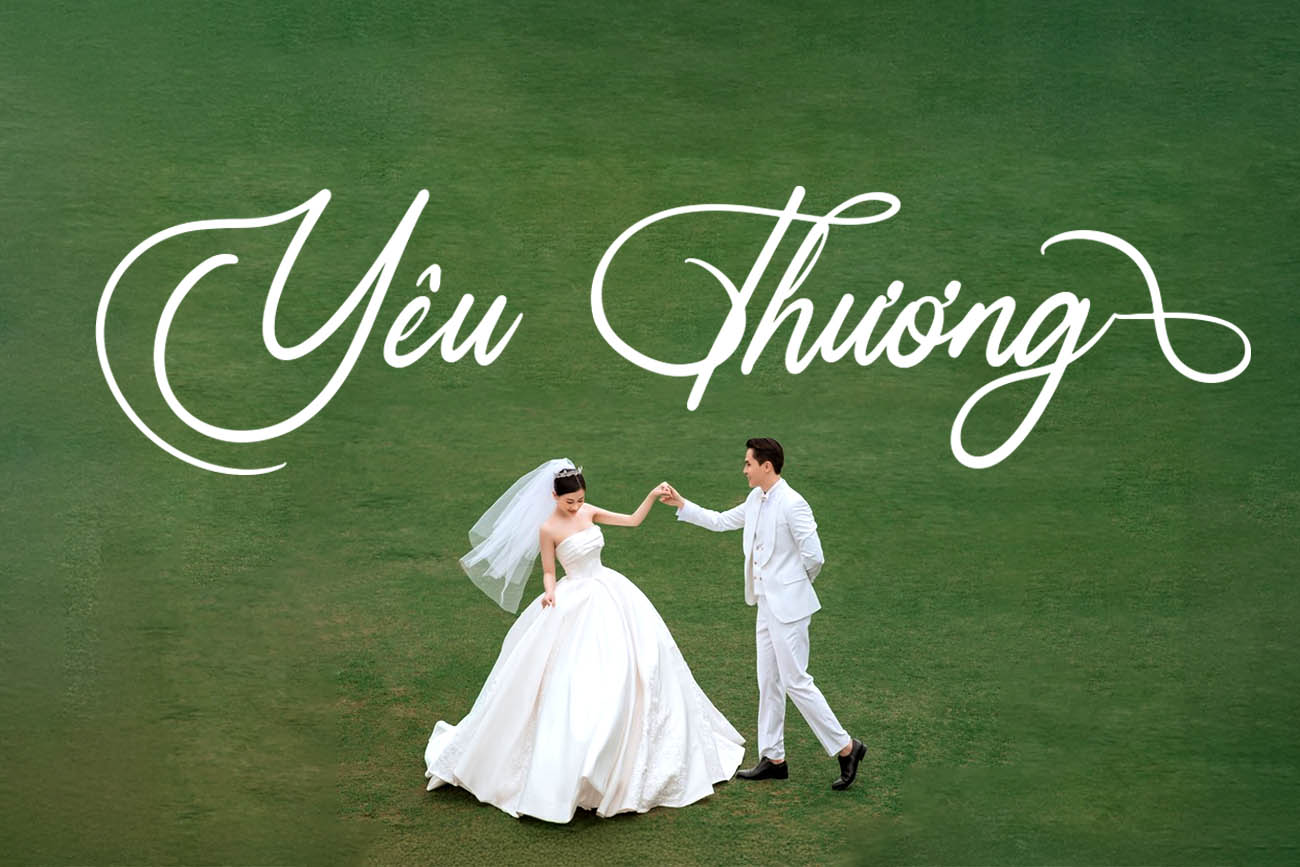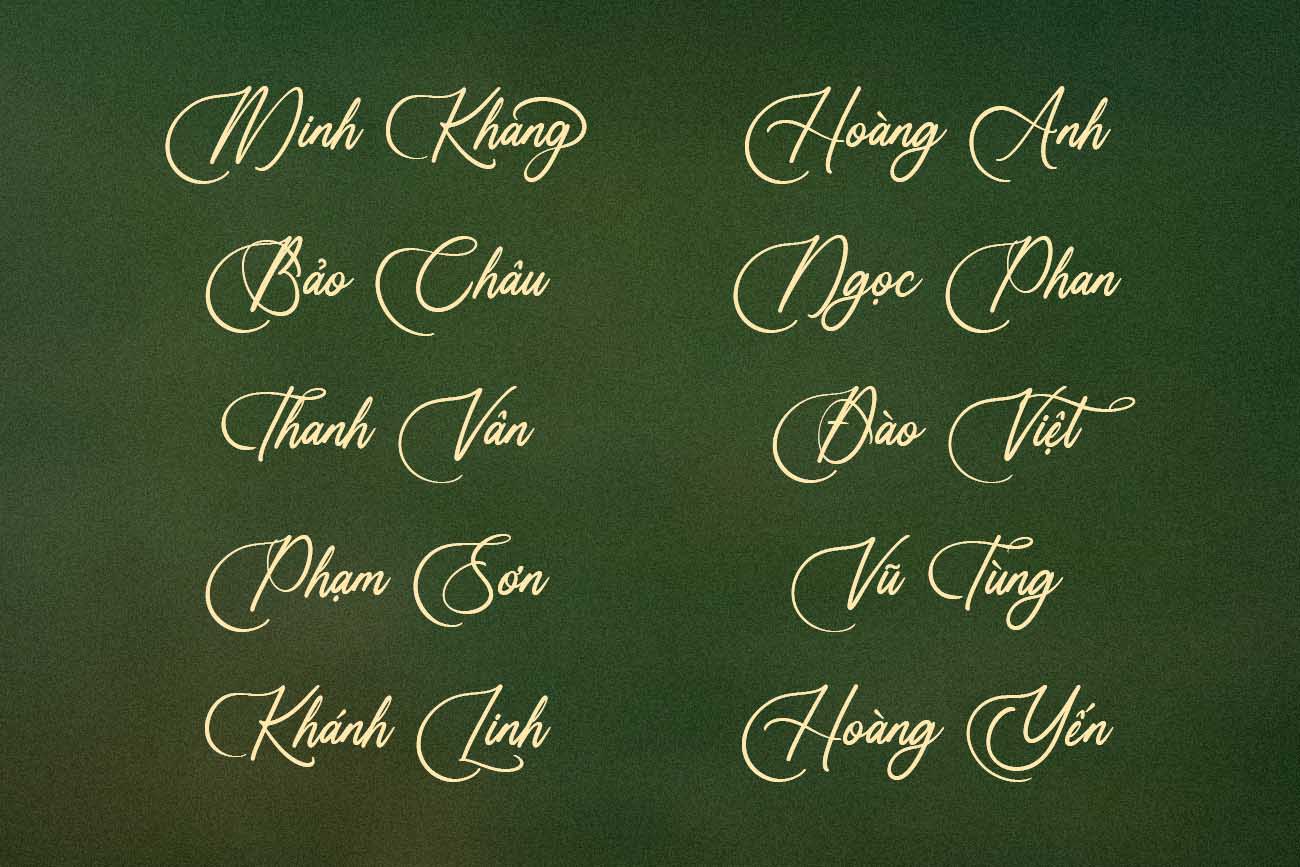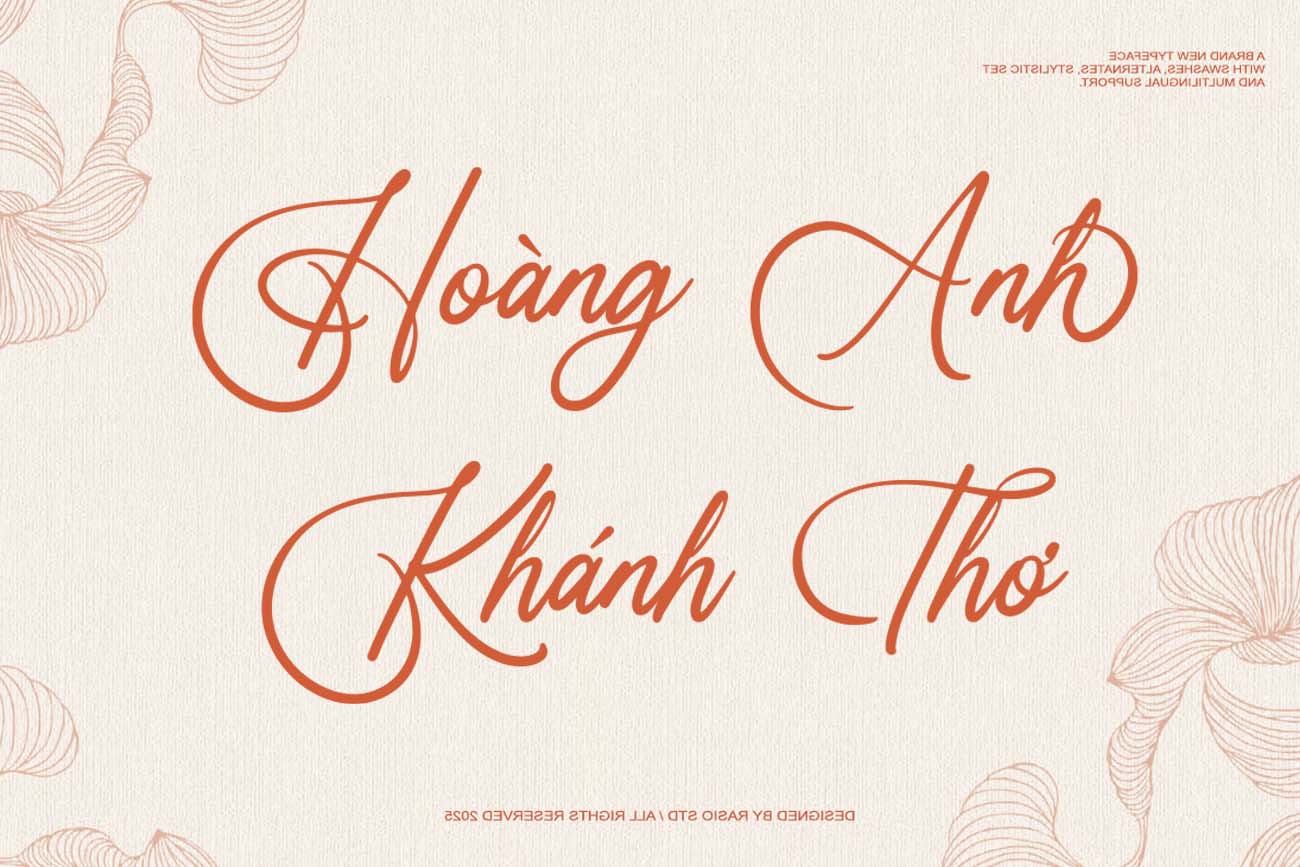
TH Uniquely Vifanite -  Font Chữ Thiệp Cưới Uốn Lượn Việt Hóa
TH Uniquely Vifanite - Font Chữ Thiệp Cưới Uốn Lượn Việt Hóa
Tác giả Etterena studio
Trong thiết kế đồ họa, đặc biệt là mảng thiết kế sự kiện và lễ cưới, việc lựa chọn đúng kiểu chữ quyết định đến phần lớn sự thành công của ấn phẩm. Hôm nay, chúng tôi xin giới thiệu đến cộng đồng designer một siêu phẩm mang tên TH Uniquely Vifanite. Đây là phiên bản font chữ Việt hóa hoàn hảo từ bản gốc Uniquely Vifanite do tác giả *Etterena studio* sáng tạo, hứa hẹn sẽ mang lại sự thăng hoa cho các dự án thiết kế của bạn.
Vẻ Đẹp Tinh Tế Của TH Uniquely Vifanite
Mang trong mình phong cách script hiện đại kết hợp với calligraphy, TH Uniquely Vifanite nổi bật với các đường nét thanh đậm vô cùng mượt mà. Là một font chữ uốn lượn đầy tính nghệ thuật, từng ký tự trong bộ phông này đều được chăm chút tỉ mỉ để tạo ra sự kết nối liền mạch, mang lại cảm giác lãng mạn, bay bổng và vô cùng sang trọng. Chính nhờ đặc tính thị giác tuyệt vời này, nó được giới chuyên môn đánh giá là một font chữ đám cưới lý tưởng, giúp tôn lên vẻ đẹp trang nhã cho mọi ấn phẩm trong ngày trọng đại.
Lý Do Nên Lựa Chọn Phiên Bản Việt Hóa Từ TH Team
Trước đây, việc ứng dụng các phông chữ mang phong cách phương Tây thường gây khó khăn cho designer Việt Nam do tình trạng lỗi dấu câu. Tuy nhiên, thông qua bàn tay tỉ mỉ của đơn vị thực hiện là TH Team, phiên bản TH Uniquely Vifanite đã giải quyết triệt để vấn đề này. Hệ thống dấu tiếng Việt được TH Team tinh chỉnh khéo léo, đảm bảo sự cân đối về mặt không gian, hòa hợp với các nét móc lượn mà vẫn giữ nguyên trọn vẹn tinh thần của bản gốc.
Giờ đây, các nhà thiết kế có thể tự do gõ tiếng Việt mà không cần tốn thời gian vẽ lại dấu. Nếu bạn đang tìm kiếm một font chữ thiệp cưới đẳng cấp để làm hài lòng những khách hàng khó tính nhất, hay một font chữ cưới chuyên dụng cho các hạng mục như menu, bảng welcome, backdrop chụp ảnh, thì TH Uniquely Vifanite chính là mảnh ghép hoàn hảo không thể bỏ qua.
Lời Kết
TH Uniquely Vifanite không chỉ đơn thuần là một công cụ văn bản mà còn là một tác phẩm nghệ thuật giúp nâng tầm dự án thiết kế của bạn. Sự kết hợp giữa đường nét nguyên bản của Etterena studio và kỹ thuật Việt hóa chỉn chu từ TH Team chắc chắn sẽ mang lại trải nghiệm thiết kế tuyệt vời.